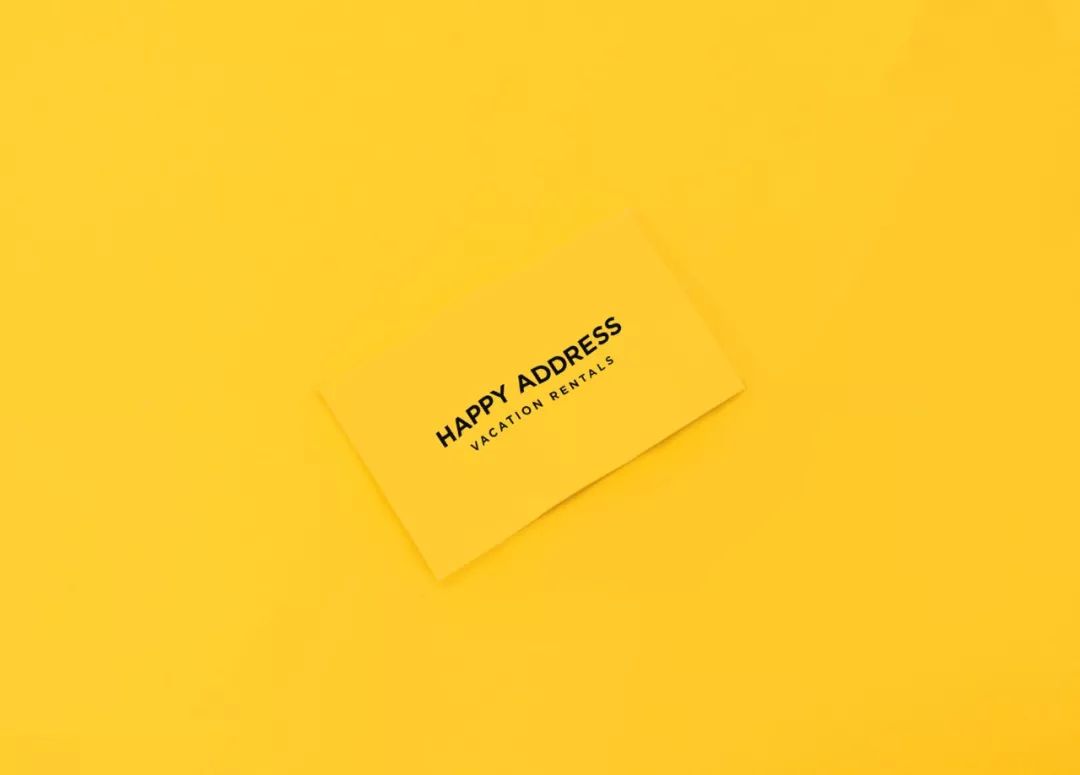
这家设计团队,凭啥四次被Behance推上热门?
好看的字体总能第一时间吸引眼光
Address Sans 的无衬线字体,由Sudtipos字体公司创始人之一Ale Paul和Futura团队共同开发,其灵感根植于20世纪50年代初的德国街头招牌字。
常常关注字体设计的话,对Sudtipos字体公司的作品应该不陌生,Sudtipos为许多企业形象、广告、产品包装提供字体方案, 他们的字体曾出现在可口可乐和李维斯的宣传活动中,以及《纽约时报》的报道中。
不过今天要介绍的不是Sudtipos字体公司,而是Futura设计团队。
这家来自墨西哥设计团队Futura ,他们的项目在Behance上的人气达到300万+之多,作品的关注度极高。只要你最近上过Behance首页,一定对他们的作品有印象,他们作品的辨识度和质量都很高,一连4次被Behance推荐上首页热门,其中的Motín咖啡店视觉形象设计收获了超过了2万+浏览。
可以说,他们是当代设计师必关注的设计团队之一,我极力推荐他们的作品,不仅是因为他们高质量的作品,还有他们的坚定的设计理念。
坚定的设计理念
企业的文化,决定于理念,也成就了产品。即是是设计团队/工作室也不例外,在Futura的网站首页,首先吸引你的是一张摄影作品和一段文字:
Our work willlast longer than us.We have always been here, but now we are stronger than ever.
We are a creative studio and we want to change the world. We wish we could find the cure for cancer but we won't. Instead we create great brands, provocative images, beautiful objects, comfortable spaces and user-friendly interfaces. That’s our way to improve the quality of life of those we reach.
We are Futura, a brand after all.
大概的意思是:
我们的作品会比我们活得更久。
我们一直在这里,但现在的我们比以往更强大。
我们是一个创意工作室,我们想改变世界。 我们希望我们能找到治愈癌症的方法,但我们不会。 我们创造了伟大的品牌、具激发性的图像,美丽的物体,舒适的空间和友好的用户界面。 这是我们所能做到的改善我们生活质量的方法。
毕竟,我们是Futura,一个品牌。
在Futura,他们有四大原则:
Rule No. 1
Never work for politicians, religions or gambling institutions.
原则一:永远不为政客、宗教或赌博机构工作。
Rule No. 2
Be firm, determined, persevering and almost obstinate when it comes to good design.
原则二:在好的设计上要坚定、坚持不懈、近乎固执己见。
Rule No. 3
Push the limits, propose more and exceed expectations.
原则三:突破限制,提出更多,超越预期。
Rule No. 4
Always choose nice people, great projects and experimentation above money.
原则四:将好项目,善意的人置于金钱之上。
高质量的作品
Motín咖啡店
Motín是一家位于墨西哥城美食界最时尚的街区之一Colonia Roma的咖啡店,从品牌命名、视觉形象到室内设计都由 Futura 负责。
Superthing是位于美国德克萨斯州奥斯汀的咖啡品牌,对比当前咖啡行业美学,极简和缺乏色彩的流行美学,Futura 创造出独特鲜明的产品形象,期待将品牌带到另一个极致。
Superthing这个名字是Futura创作过程的起点,通过尝试定义“Superthing”实际上是什么。
Logo 本身也是一种superthing,将其设定为一个动态的标识,在不同的包装型态中变换着;让Logo 中的英文字母很恣意地凸显于每个精彩的包装设计当中。
他们的解决方案是创建一个动态的标识,LOGO本身就是一种“Superthing”,在不同的包装中变换形态,LOGO中的英文字母穿梭于包装设计当中。
Address Sans. Specimen collaboration.
这一款名叫 Address Sans 的无衬线字体,有着复古美学的味道,又不失现代工业的时尚。 Address Sans 由Sudtipos字体公司创始人之一Ale Paul和Futura团队共同开发,其灵感根植于20世纪50年代初的德国街头招牌字。
SIMCA地产视觉
SIMCA是一家致力于战略和建设的房地产开发商,主要在墨西哥的Merida,Cancun,Playa del Carmen和Tulum。
LOGO以字体为主,可读性强,作为开发商的SIMCA本身就包含多个品牌,所以选择一种同时充满活力的醒目色调,代表着力量和现代感。
Raw寿司吧品牌视觉
Raw是位于科威特的寿司吧。 它的灵感来自传统的日本料理和高品质的标准,保留了古典文化的一些细节,以复古图像为代表。
黑色笔触代表了主人,一位年轻的科威特人,也是主厨,代表他对料理的执着和高标准。单色配色方案,阿拉伯语和日语排版选择,以及形成“RAW”一词的笔触都具有男性化的个性,可以通过他们提供的美味佳肴来抵消。
“Kintsugi”作为餐具,这是一种日本的工艺技术,用金粉,银粉或铂金修复破碎的陶器。
Happy Address度假租赁公司
“Happy Address”是一家在墨西哥的PlayadelCarmen和Tulum经营度假租赁的公司。
这个项目有两个用户群:业主和租赁房产享受美好假期的人。
Futura团队创建这家公司的名字是基于这样一种感觉:当你是业主,你的房产会给你钱(是不是很快乐),当你在墨西哥海滩度假时,你可以肯定地把这个地点称为“Happy Address”(你正在享受快乐
)。
作为品牌解决方案的一部分,色调、版式和插图代表着纯粹的快乐。一起来感受一下快乐。
Toro西班牙餐厅
Futura团队与JWalk合作,为一家位于纽约、波士顿、曼谷和迪拜的西班牙餐厅Toro重新设计。
在不太明显的情况下传达西班牙的氛围,因为Toro这个名字很容易解释。
因此,对于品牌,他们从西班牙文化的一些元素中获得灵感。一方面,他们重新诠释了毕加索的Guernica(格尔尼卡)与西班牙最具标志性的节日之一:圣费姆。另一方面,他们从高迪的马赛克技术——特伦卡迪斯那里得到灵感。
颜色的选择和版式的处理与餐厅的场景相关,因为这不是一家传统的西班牙餐厅,这是一个充满创新的地方,为那些想享受美好时光的人,享受美食和好酒的人。
Futura 团队对设计的执着和认真的态度非常值得我们学习。